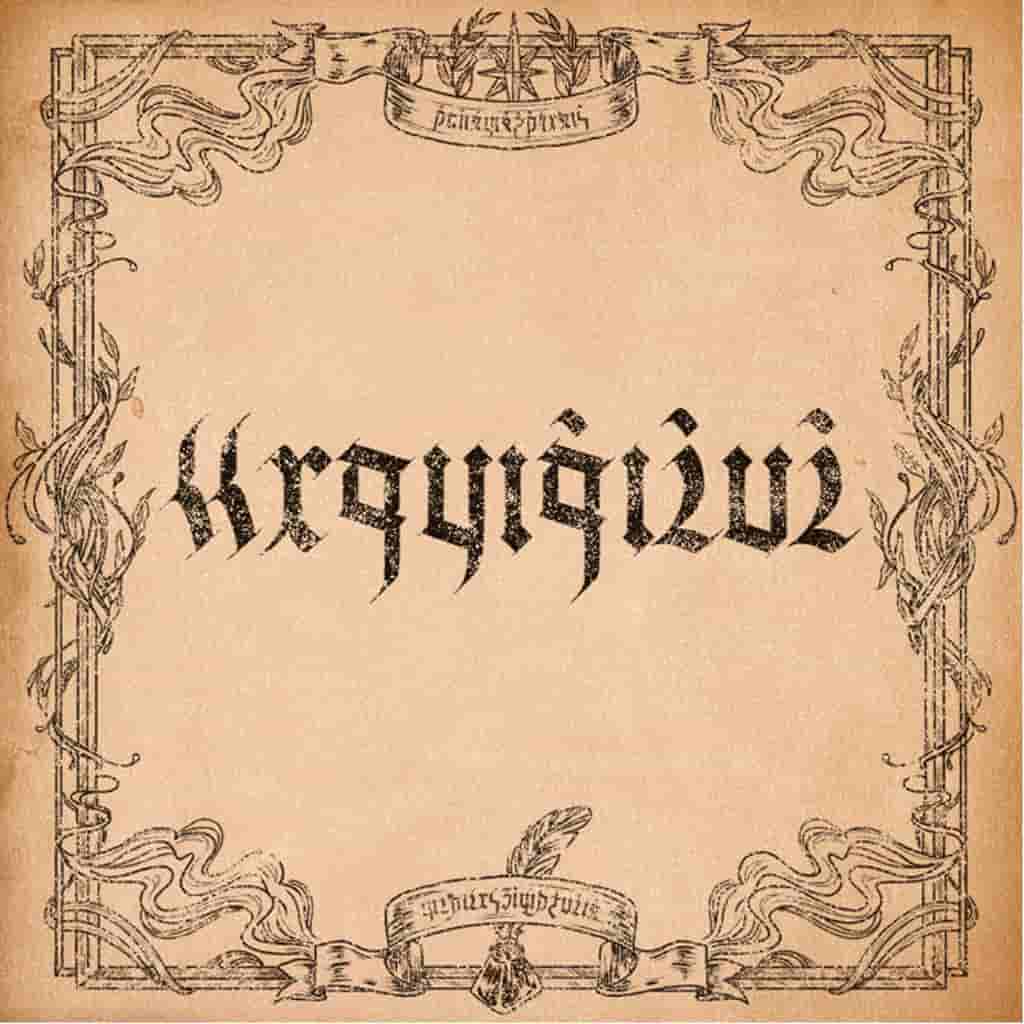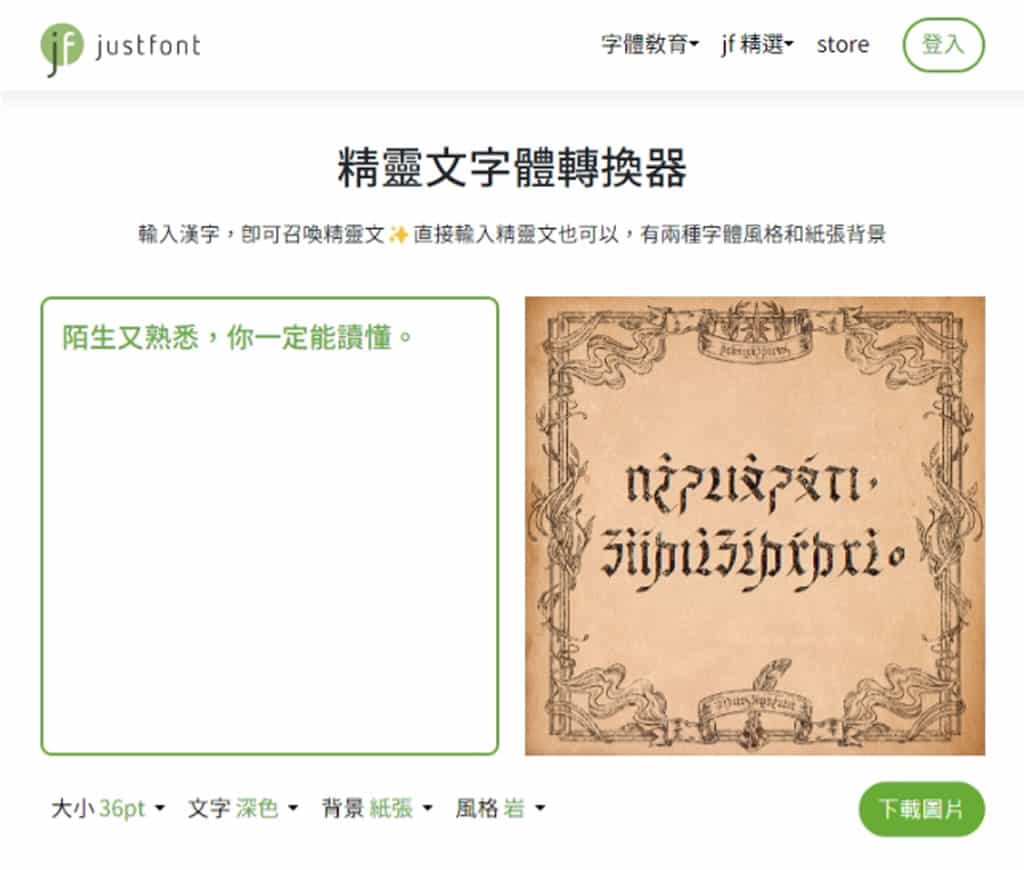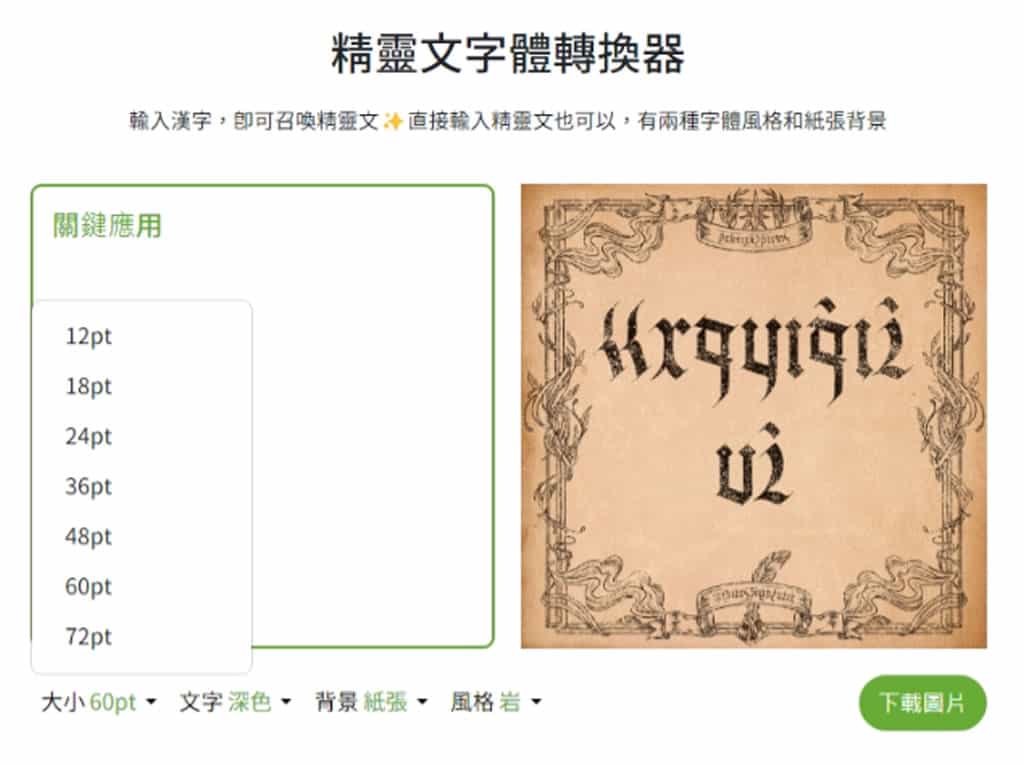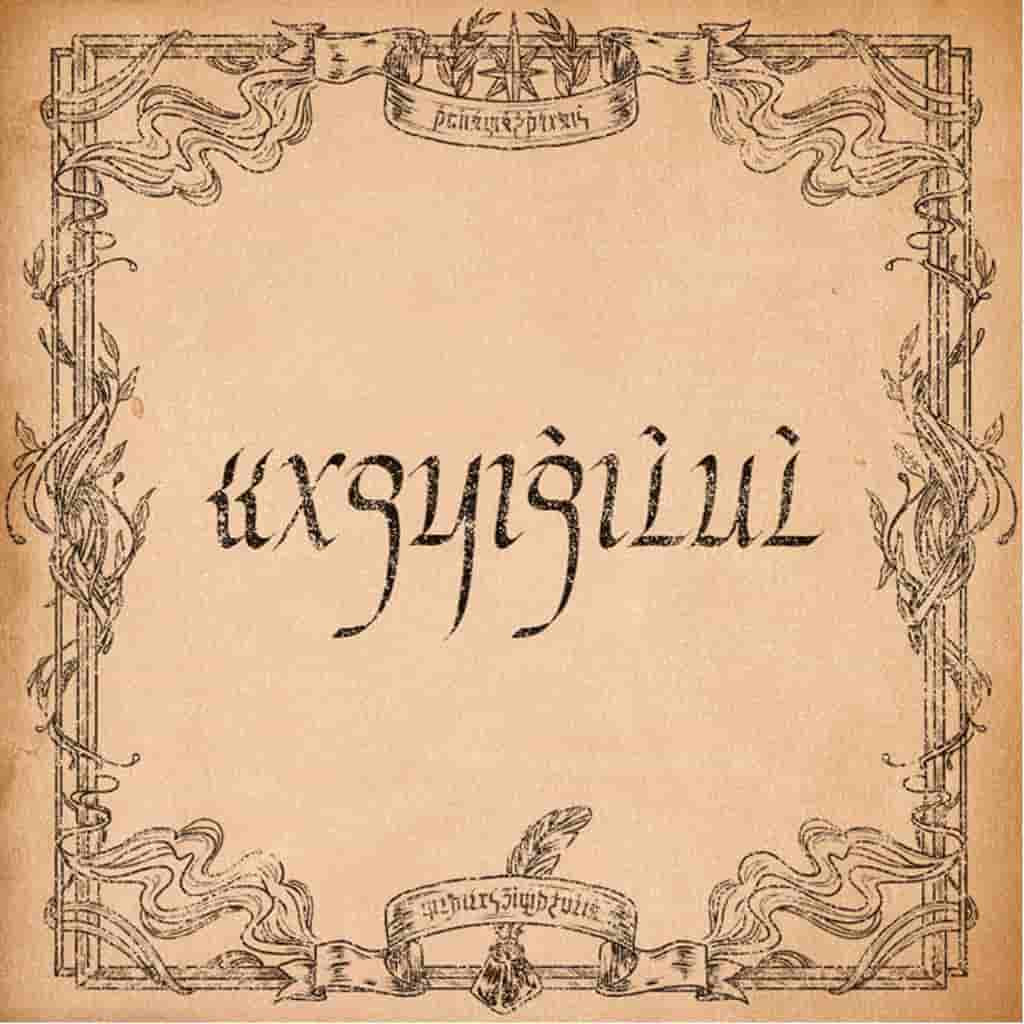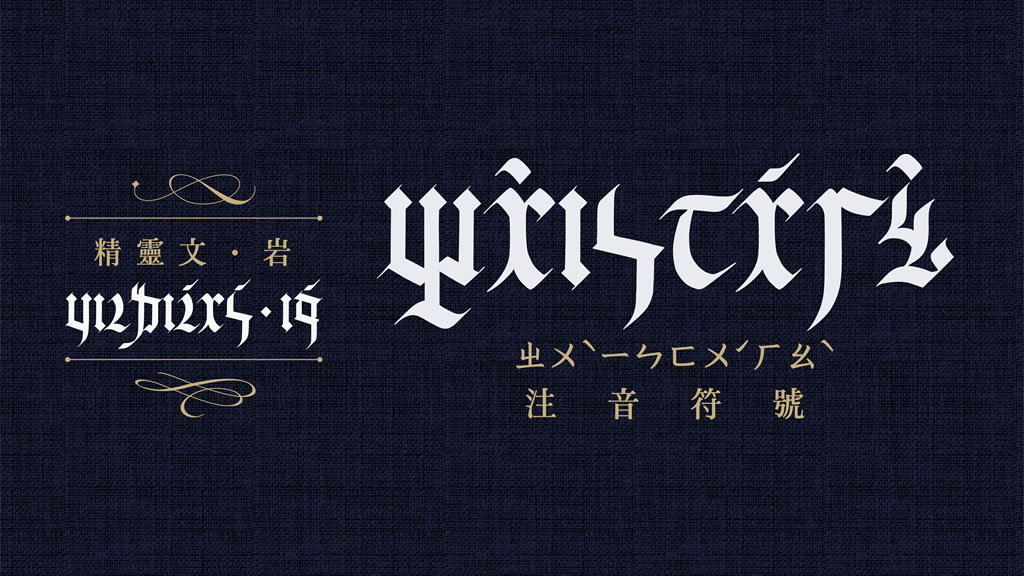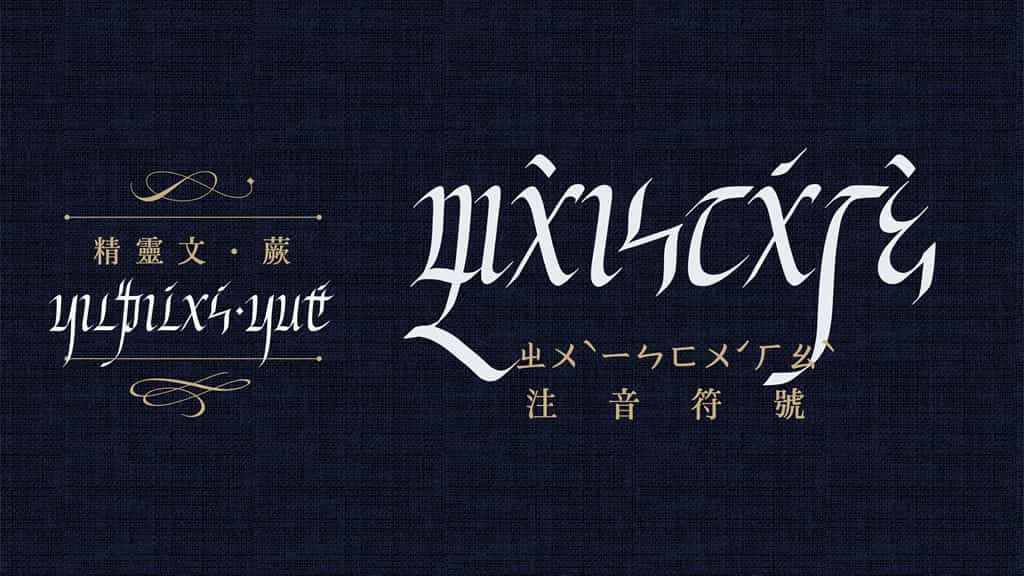
「精靈文字體轉換器」是由 justfont 推出的免費線上工具,主要功能是將注音文轉換成具有「精靈文」風格的獨特文字。使用者只需按照日常習慣輸入注音,轉換器便會將其轉換成如密語般的樣式,呈現出奇幻的精靈文字效果。這款字型創意地重新定義了ㄅㄆㄇ 注音字母,被形容為「台灣人才懂的史詩注音字型」,更增添了本地文化的趣味。
根據 justfont 網站的說明,這款精靈文字體是由書法家 Daphne 精心設計,以手寫方式創作了兩種造型風格:「精靈文.岩」與「精靈文.蕨」,營造出宛如台灣人專屬的奇幻密語。此外,轉換器還提供了由 Daphne 設計的紙張背景,使輸出的文字更具視覺效果。
輕鬆將注音文變身為「精靈文」!支援線上轉換及 Windows 字型下載,帶來專屬台灣的奇幻書寫體驗
1.進入「justfont 精靈文字體轉換器」網站,就可以直接在綠色文字框之中輸入一般的中文文字。
2.文字框的底部,可以自由選擇切換深淺色、字體大小與「精靈文・蕨」以及「精靈文.岩」兩種字體,甚至還可以更換由做作的 Daphne 所創作的背景圖。
3.下圖是使用「精靈文.岩」所產生的效果圖。
4.下圖是使用「精靈文・蕨」所產生的效果圖。
如果細看所產生的效果圖,其內容就是以注音符號加上四聲所組成,但透過「精靈文・蕨」以及「精靈文.岩」兩種字體所形成的效果就像古老的密文,為注音符號增添了另番的趣味。